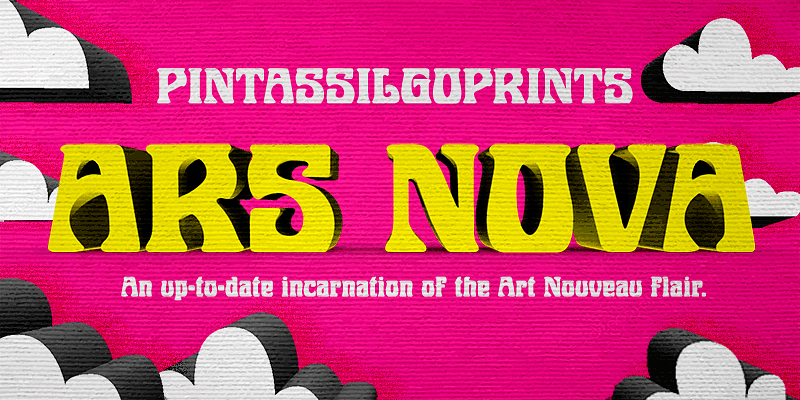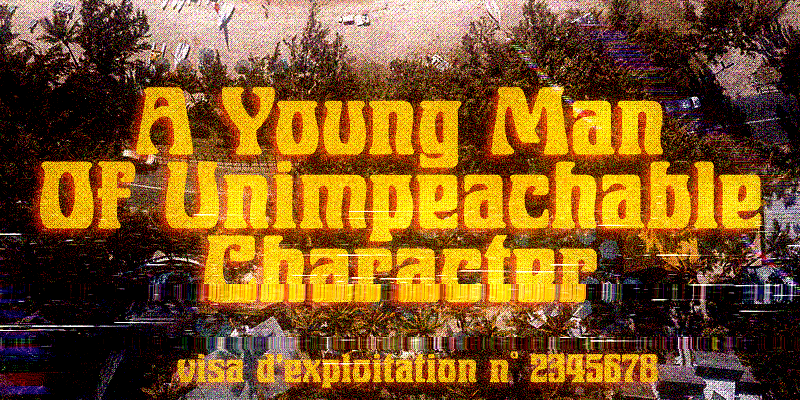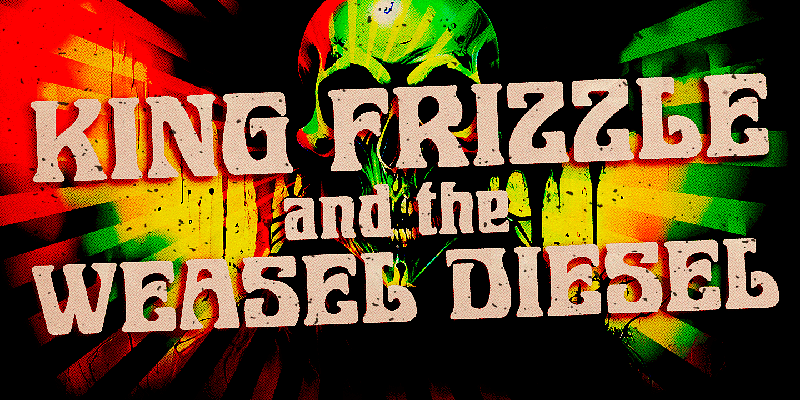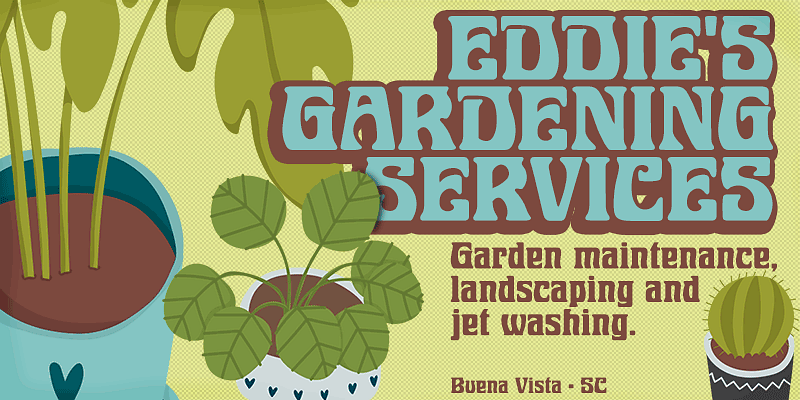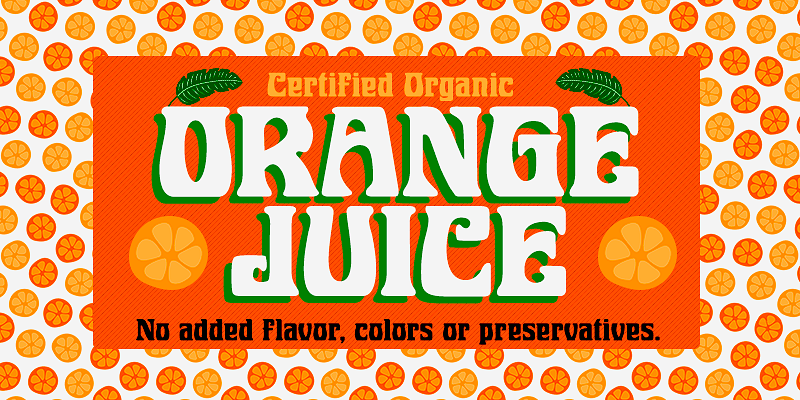
PintassilgoPrints est une fonderie de polices numériques basée au Brésil, fondée en 2009 par Erica Jung et Ricardo Marcin. Son catalogue de typographies éclectiques et artistiques, chacune caractérisée par un style distinct et une créativité certaine, a fait la renommée du studio. Des scriptes pour les invitations, avec empattement pour les titres, sans empattement pour les affiches… Vintage et rétro, fantaisiste et ludique, en lettrage ou en calligraphie : les possibilités d’expression et d’originalité sont infinies pour les créatifs et les designers.